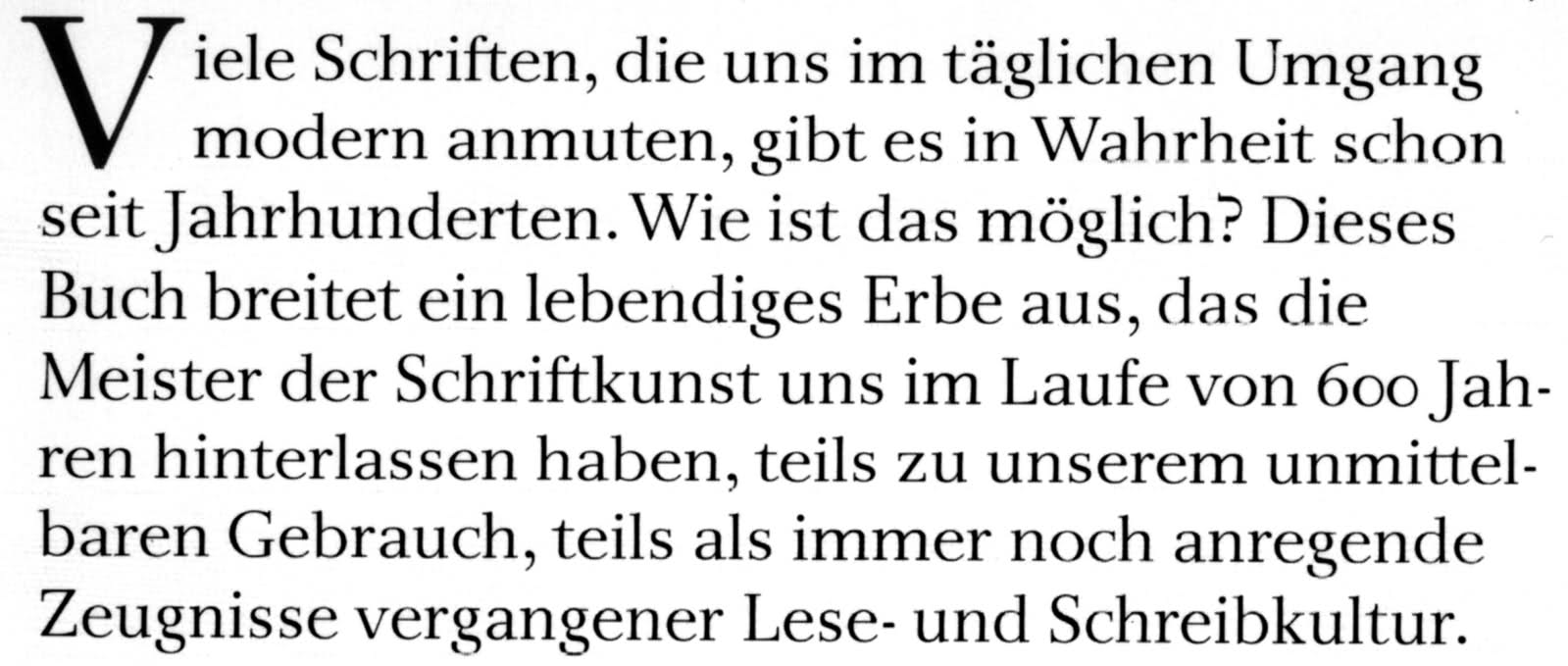
Spätbarock? Frühklassizismus? suche alternativen zur lucinde
Hallo allerseits. Ich suche eine Alternative zur Lucinde. Die Lucinde ist eine wunderbare Schrift von Axel Bertram, zu sehen in seinem Buch "Das wohltemperierte Alphabet" und in Veröffentlichungen vom Lehmstedtverlag Leipzig, die Axel Bertrams Sohn gestaltet. Die Schrift gibt es leider nicht zu kaufen. Ich hab bei Axel Bertram angefragt, der seit drei Jahren immer wieder die gleiche Auskunft erteilt: er hat die Schrift an Linotype zwecks Veröffentlichung gegeben und darf deshalb nicht verkaufen - der Font soll demnächst dort erscheinen. Seit über drei Jahren erscheint die Lucinde also demnächst bei Linotype. Ich hab mittlerweile den Glauben dran verloren und suche nun also nach Alternativen.
Was ist das Besondere an der Lucinde? Sie ist eine Leseschrift zwischen barocker und klassizistischer Antiqua: nicht ganz so steif und vornehm wie Didot und Co., aber deutlich gerader und feiner als Baskerville & Genossen.
Wunderbar zu lesen, auch in kleinen Graden. Schönes Druckbild auch auf raueren Papieren, weil die Serifen und Haarstriche nicht ganz so fein ausfallen - im Gegenatz zu den klassischen klassizistischen Schriften.
Laut Axel Bertram soll die Schrift auch recht sparsam im Platzverbrauch sein, obwohl sie wirklich nicht besonders schmallaufend aussieht.
Sowas suche ich. Als Textschrift für feinen Mengensatz feiner Prosa aus dem 19. Jahrhundert. Also brauch ich einen Regularschnitt mit echten Kapitälchen und einen dazu passenden Kursivschnitt. (Halbfett, Fett, Titling, Condensed etc. nutze ich für sowas sowieso nicht; wenn es aber einen halbfetten Schnitt zusätzlich geben sollte, wäre es umso besser).
Was Spätbarockes oder Frühklassizistisches?
Ich bin sehr gespannt, weil ich schon ziemlich lange nach soetwas suche und bisher noch nichts der Lucinde Vergleichbares gefunden habe ... sehr seltsam angesicht tausender verfügbarer Schriften.
ich fürchte den meisten hier geht’s wie mir: kannst du vielleicht einen scan der lucinde reinstellen? dann tun wir uns alle leichter.
ohne jetzt was gesehen zu haben und nur auf grund deiner beschreibung: würde dir die corporate A passen?
ist halt eine moderne interpretation deines themas
(wenn ich das richtig verstanden habe) :roll:
Die DTL Fleischmann sieht ganz gut aus und kommt meinen Intentionen schon sehr nahe, ist aber sauteuer. Die Romain war ein guter Tip. Auf der Webseite der Schriftenschmiede der Romain wird noch eine der Lucinde näherkommende neue Schrift angekündigt: eine NEW FOURNIER, die sehr verheißungsvoll aussieht, aber wohl auch erst im Entstehen ist. Ich werde das mal im Auge behalten.
Die Corporate A hatte ich auch schon mal in Erwägung gezogen, aber sie gefällt mir nicht wirklich, die Mittelhöhe ist zu hoch, sie sieht irgendwie sehr kalt aus und außerdem finde ich Firmenschriften von Großkonzernen in feingeistigen Büchern nicht so prickelnd. Die Bulmer ist ganz schön, aber eigentlich auch nur eine typische klassizistische, von der etwas robusteren Sorte.
Von der Lucinde hab ich versucht einen Scan zu machen - ich versuch ihn mal hier rein zustellen - hab das noch nie gemacht - entschuldigt etwaige Qualitätsmängel. Ihr könnt auch unter http://www.lehmstedt.de die schrift sehen - im Verlagsnamen und bei einigen Büchern.
Mir gefällt halt wahnsinnig, wie schön die Textschrift läuft. Die Versalien sind gar nicht so spektakulär, aber die Gemeinen bestechen m.E. durch ihre sehr schönen kalligrafischen Strichdicken, die sie vermutlich so sehr von den steifen klassizistischen Klssikern unterscheiden. Ist nur ne Vermutung, ich bin nur Schriftanwender und kein Entwerfer. Herr Bertram hat mir mal verraten, dass der Ausgangspunkt seines Entwurfes eine Schreibmaschinenschrift gewesen sei ... was man gar nicht vermuten möchte.
beim lesen deines ersten beitrags ist mir gleich die baskerville eingefallen, bis du sie später erwähnt hast bzw. ausgeschlossen hast. jetzt wo ich deinen scan sehe ist sie mir wieder eingefallen. vielleicht doch einen blick wert? von der anmutung halbwegs nahe?
Ja, stimmt schon, die ITC New Baskerville kommt der Sache sehr nah. Ich hab halt bisher immer ne andere, etwas gröbere Baskerville, mehr dem Bleisatzoriginal entsprechende vor Augen gehabt ...
Baskerville ist eben nicht gleich Baskerville,
Hast Du Dir die Schrift von Betatype, die ich oben erwähnt hab, angeschaut? Schau auch mal bei Elsner+Flake, da gibt’s für 40,–/Schnitt die Typoart-Fassungen von Fleischmann und Fournier. Die unterscheiden sich zwar ziemlich von der (wirklich hübschen) Lucinde, aber vielleicht gefällt Dir ja eine davon trotzdem?
schaumermal.
Lehmstedt gefällt mir (nicht nur als alter Leipziger) sehr gut. Was mich wundert, das ich keine Infos zu Schriften von Axel Bertram finde, es gibt ausser Lucinde noch Solomo, Rabenau und andere Schriften. Oder doch und ich finde es nur nicht?
schöner thread- es macht mal wieder spaß hier unterwegs zu sein und ja - zu diesem thema fällt mir die "Granjon" ein (linotype), eine wunderbare schrift.
Aber was ist nun mit Axel Bertram? Ich finde nichts!